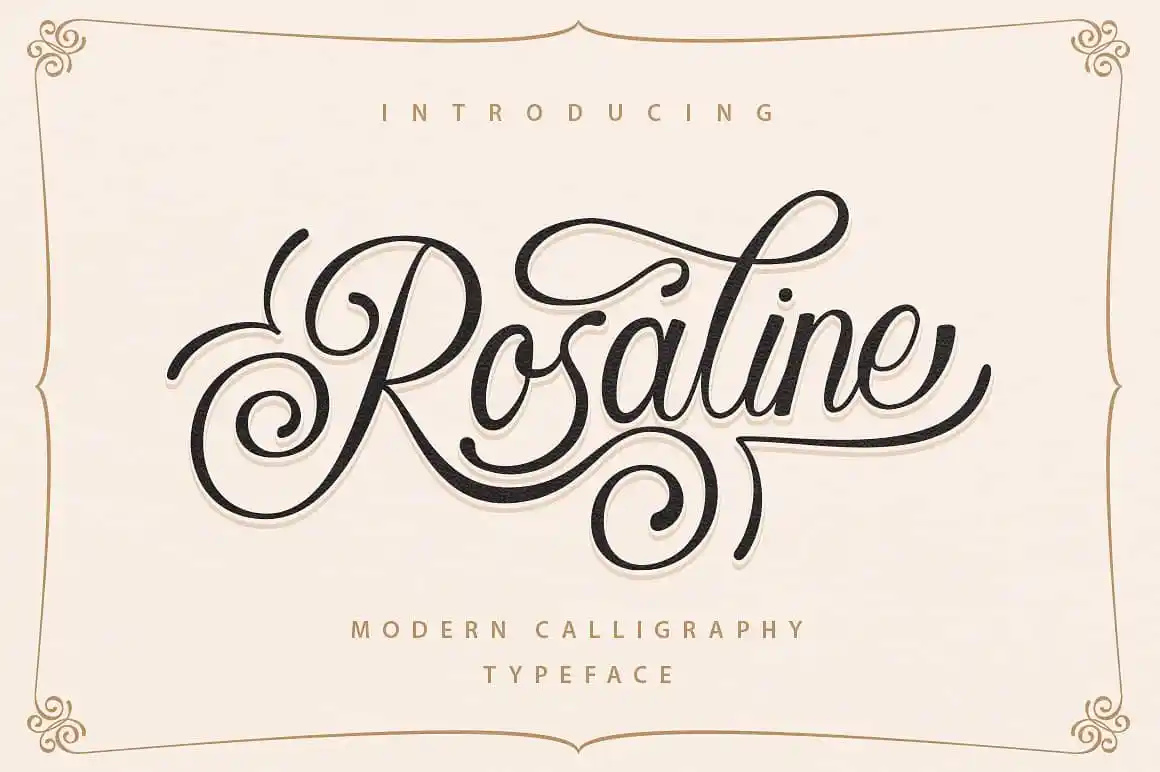
Rosaline Script Font – Download Grátis
Introduzimos a Rosaline Script Font! Desenvolvida pelo designer sizimon, esta é uma fonte premium vendida na plataforma creativemarket. Embora Rosaline normalmente custasse dinheiro, está disponível gratuitamente para download hoje. Rosaline é um tipo moderno de calligrafia. É atraente tanto para logotipos quanto para cabeçalhos de site, design de moda e até mesmo cartões de casamento. Rosaline possui um estilo elegante, incluindo um conjunto completo de letras maiúsculas e minúsculas, uma grande variedade de pontuação, números e suporte multilingue. Ideal para os mais variados usos, desde a criação de logotipos até o design de cartões de casamento. Não perca esta oportunidade para experimentar um tipo tão único e elegante.